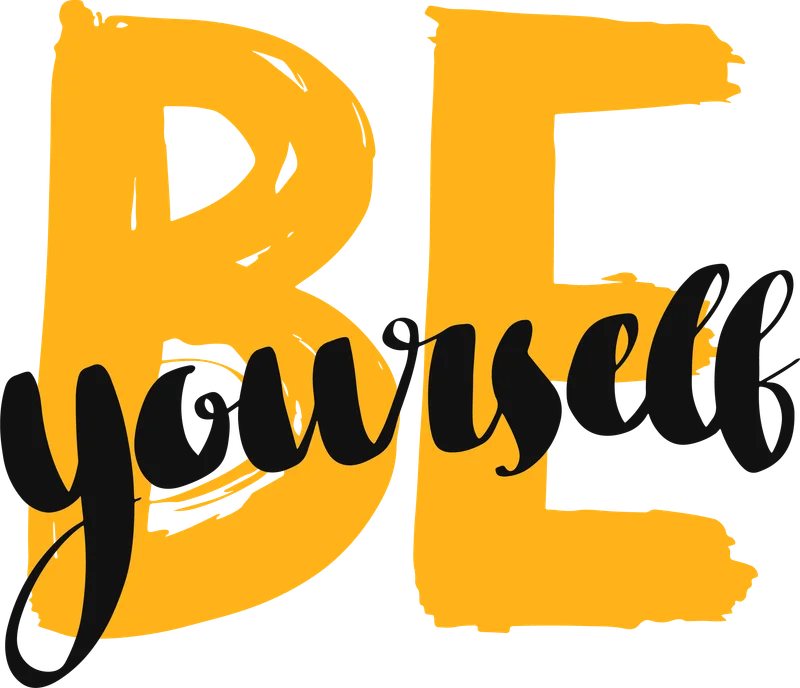
Thông điệp "Be yourself" ý nghĩa, font chữ độc đáo
Thông điệp "Be yourself" ý nghĩa, font chữ độc đáo — In hình ảnh "Be yourself" với font chữ độc đáo, truyền tải thông điệp tích cực. Phù hợp in áo thun, túi tote, sticker.
Trong hình có: chữ viết, slogan
Phong cách: flat-design · Cảm giác: khác
Tông màu chủ đạo: vàng kim, đen